상업용 무료 폰트도 종류가 아주 다양한데요. 오늘은 그중에서 활용하기 좋은 예쁜 상업용 무료 폰트를 추천해 드리려고 합니다.
1. Gmarket Sans
지마켓 산스는 G마켓에서 만든 서체인데요.
단순하고 직선적인 형태로 깔끔하고 정렬된 느낌을 주기 때문에 타이틀에 많이 사용되는 폰트 중 하나입니다.
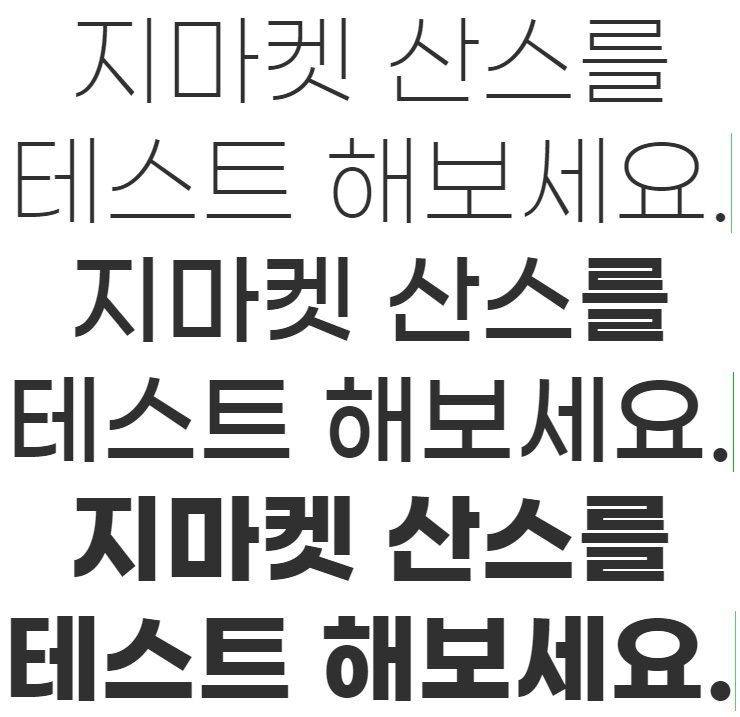
2. 레코체
레코체는 레시피 코리아에서 제작한 글꼴입니다.
강하지만 부드러운 형태를 적용한 디자인으로 타이틀로 쓰기 좋은 적당한 굵기를 가진 폰트입니다.
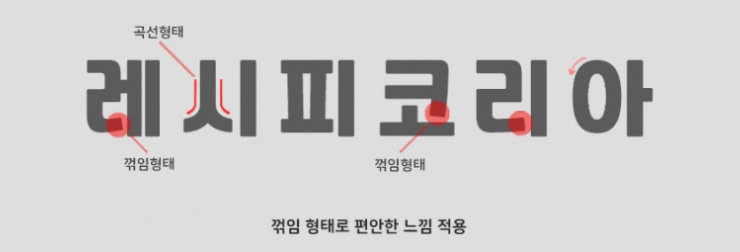
3. Rix이누아리두리체
Rix이누아리두리체는 인스타툰을 그리는 이누아리두리네와 폰트릭스가 콜라보로 제작한 무료 폰트입니다.
두꺼운 획과 부드러운 굴림이 특징으로 글씨체 자체가 동글동글하니 굉장히 귀엽고, 제목이나 강조하려는 큰 글씨에 잘 어울리는 서체입니다.
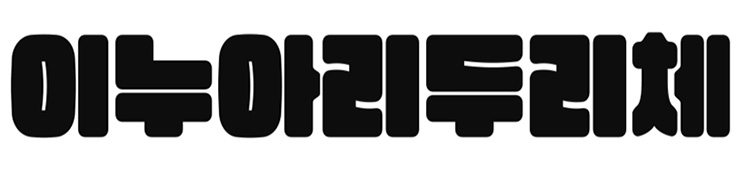
4. 프리텐다드 Pretendard
깔끔한 고딕체하면 대표적으로 꼽히면서 가장 많이 사용하는 글씨체가 바로, Noto Sans와 Apple SD 산돌고딕 Neo일텐데요.
프리텐다드는 앞서 말한 글씨체를 대체할 수 있는 정말 깔끔하고 예쁜 서체로 디자이너 길형진님이 제작한 마법같은 폰트입니다.
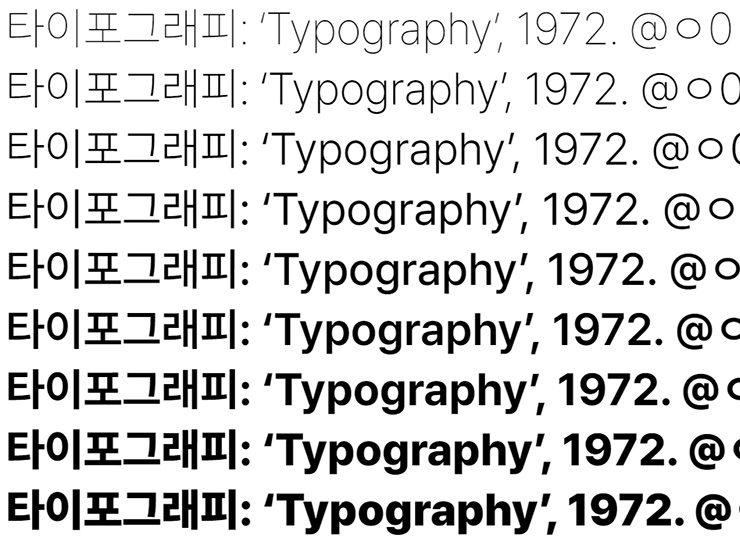
5. 에스코어 드림 S-Core Dream
에스코어 드림은 S-Core에서 제작한 꽉 찬 직사각형 구조의 서체로 9가지의 다양한 두께가 있는 글꼴입니다.
유명한 유료 폰트인 꼬딕씨 대신 많이 추천되고 있는 무료 폰트로, 제목용 글꼴로써 복고적인 형태에 현대적인 감성을 담았다고 하네요.
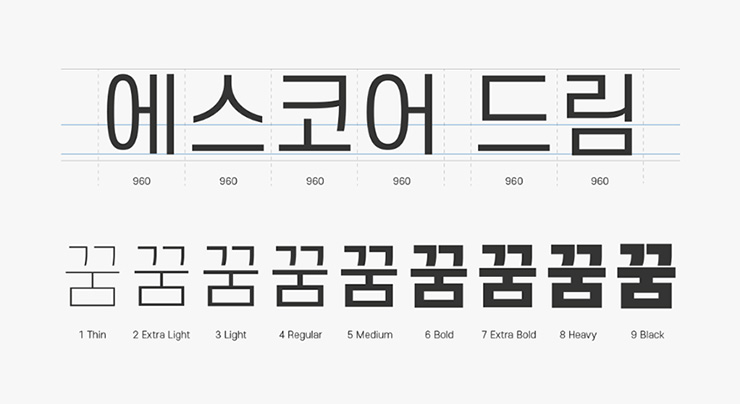
6. 티웨이 하늘체
티웨이항공 서체의 티웨이 하늘체는 제목용 볼드체로 사용하기 좋은 글씨체인데요.
레트로적이지만 모던한 느낌을 살리기 위해 세리프를 너무 강하게 표현하지 않고 단순화했다고 합니다.
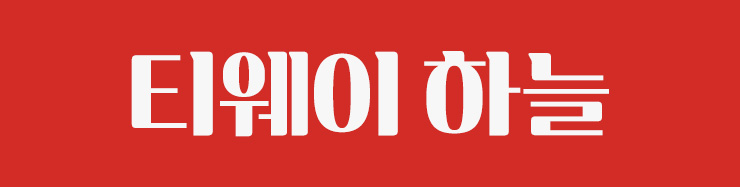
7. 여기어때 잘난체
많은 곳에서 사용하고 있는 여기어때 잘난체도 타이틀용으로 활용하기 좋은 폰트 중 하나인데요.
네모꼴의 꽉 찬 모듈로 안정적인 느낌과 동시에 경쾌함이 느껴지는 글씨체입니다.
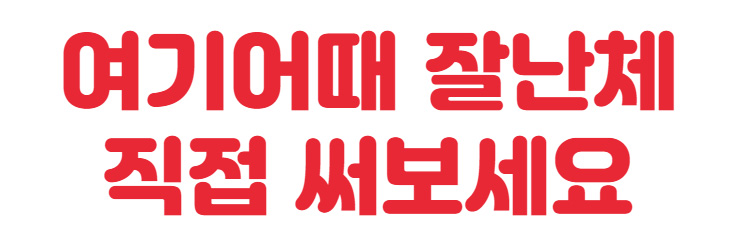
8. 강원교육모두체
강원교육모두체는 강원도 교육청과 헤움디자인이 함께 제작한 무료 서체로 강원도 행복청의 공식 서체입니다.
공모전을 통해 선정한 손글씨를 기반으로 자유로운 느낌과 높은 가독성이 특징입니다.
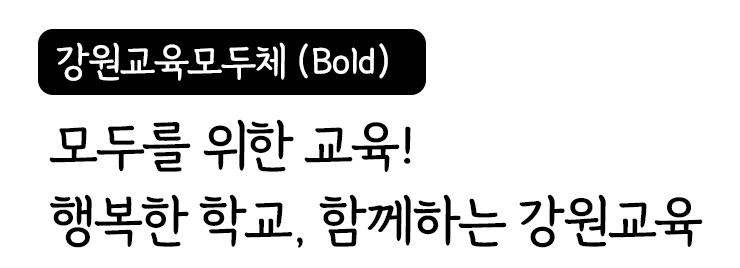
9. 배달의민족 주아체
배달의 민족 어플을 이용한다면 많이 보셨을 우아한형제들의 주아체입니다.
붓으로 직접 그려서 만든 손글씨 간판을 모티브로, 동글동글한 느낌을 주는 서체는 옛날 간판의 푸근함과 정겨움이 묻어나는 것이 특징이라고 하네요.
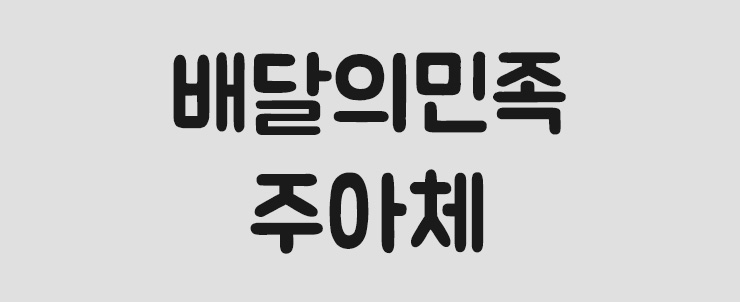
10. tvN즐거운이야기체
CJ E&M의 tvN 즐거운 이야기체도 활용도가 높은 폰트인데요.
tvN의 개국 10주년을 기념해 나온 서체로 이름 그대로 즐거워 보이는 대화체 같은 손글씨가 특징입니다.
11. 교보 손글씨
교보 손글씨 2019와 교보 손글씨 2020 박도연 서체는 교보 손글씨 대회에서 으뜸상을 수상한 분의 손글씨를 그대로 담은 디지털 서체입니다.
2019는 동글동글 사랑스러운 손글씨를 2020은 정갈한 손글씨가 눈에 쏙 들어오는 폰트입니다.
12. 카페24 무료폰트
전자상거래 쇼핑몰 플랫폼 중 하나인 카페24에서는 다양한 무료폰트를 제공하고 있는데요.
한글 폰트 중 고운밤, 써라운드, 아네모네, 당당해는 꽤 많이 활용되고 있고 좋아하는 서체라 추천드립니다.